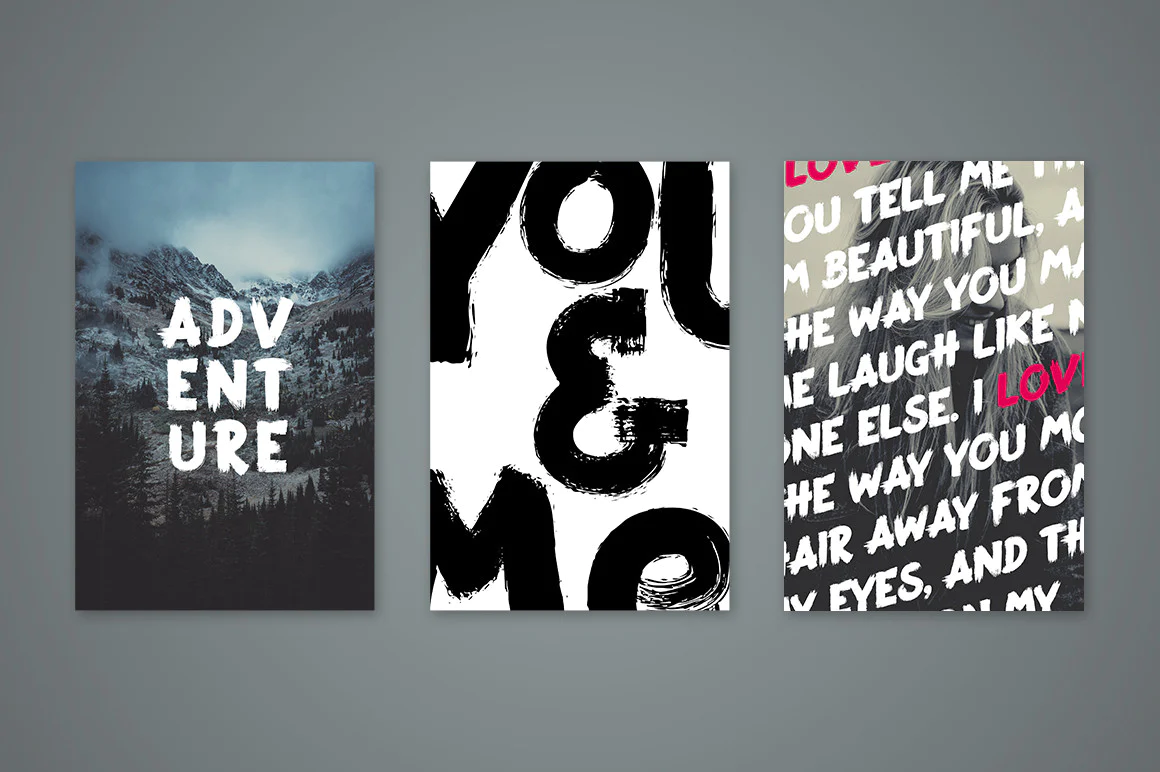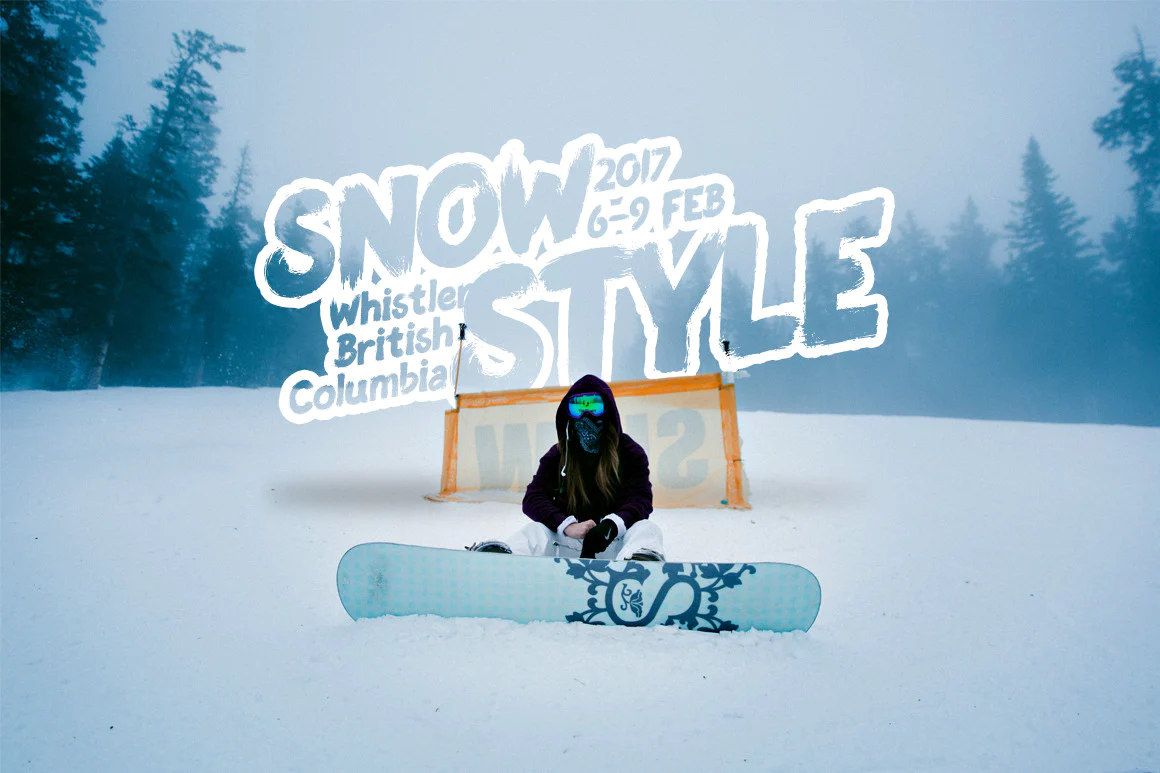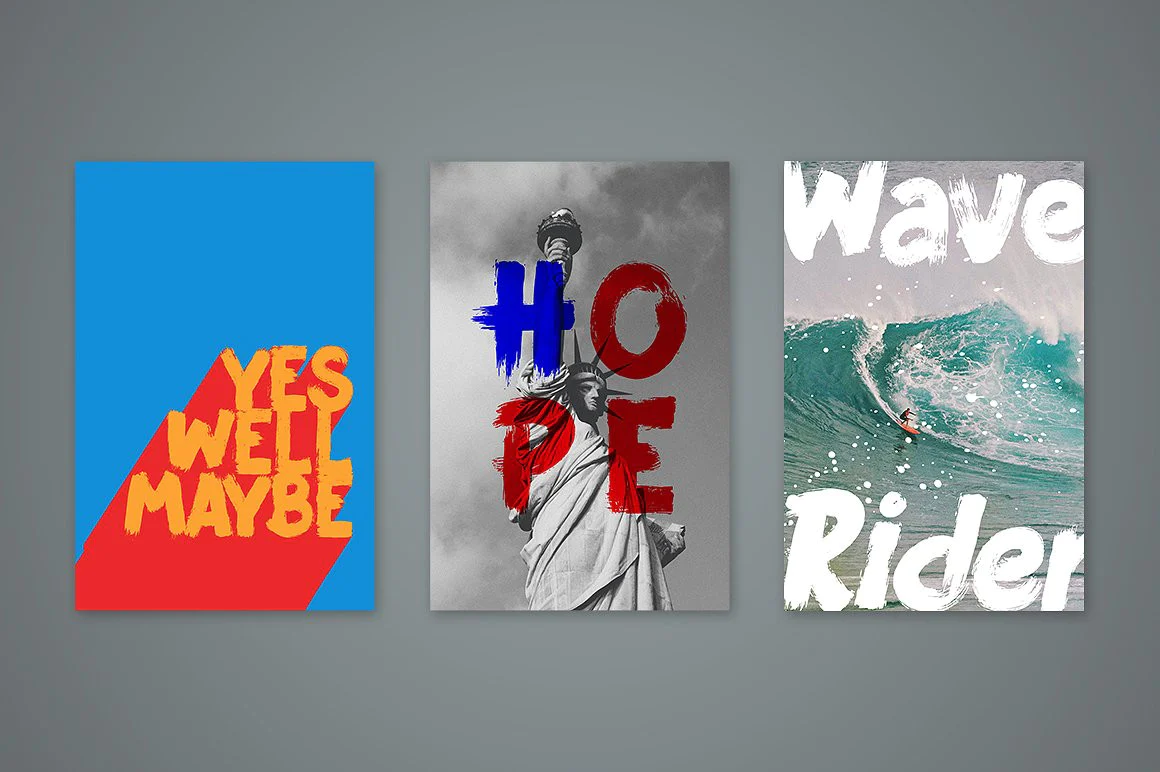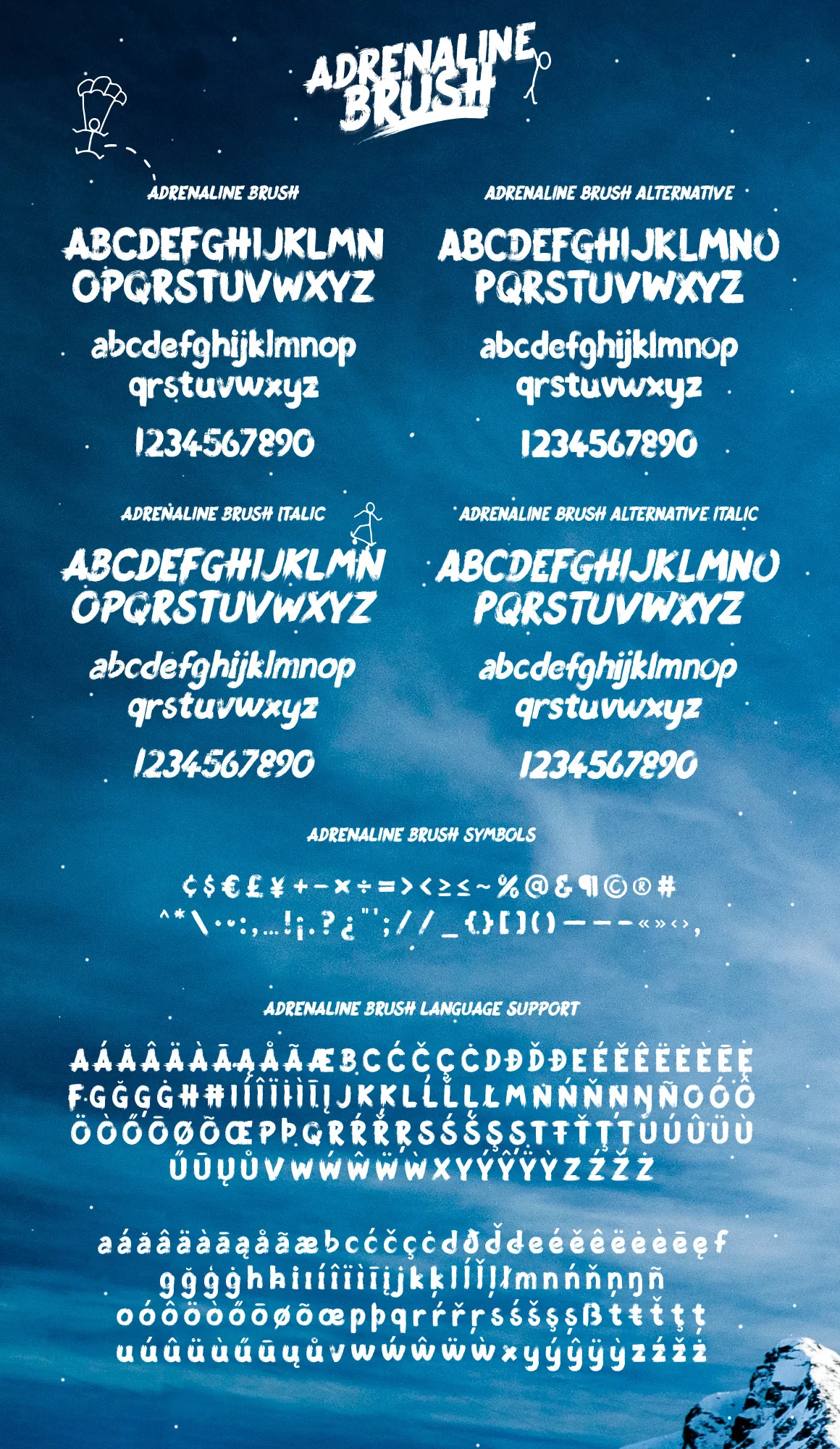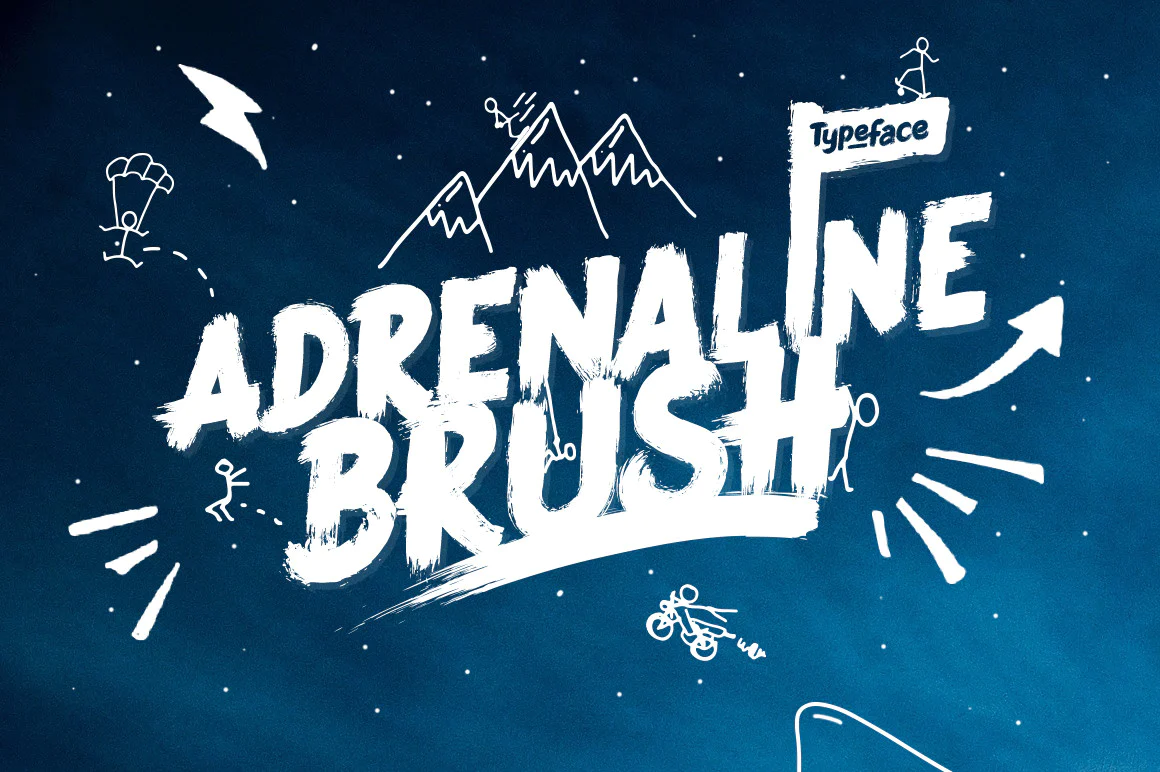
Bạn đã sẵn sàng để thưởng thức Adrenaline Brush chưa ! Một kiểu chữ không gây sợ hãi hoặc không có giới hạn về mục đích sử dụng của nó. Táo bạo và thú vị, nó sẽ tạo thêm nét cá tính tuyệt vời cho công việc thiết kế của bạn.
Bàn chải Adrenaline Đi kèm với 2 phiên bản chữ hoa / chữ thường / chữ số, để bạn có được vẻ ngoài được chải bằng tay chân thực.
1. Adrenaline Brush Đối với những người có chương trình hỗ trợ OpenType có thể truy cập các ký tự thay thế từ bên trong chương trình này.
2. Adrenaline Brush thay thế Dành cho những người không có quyền truy cập vào Opentype. Chữ hoa và chữ thường cộng với số.
- Phạm vi rộng lớn của dấu câu và ký hiệu